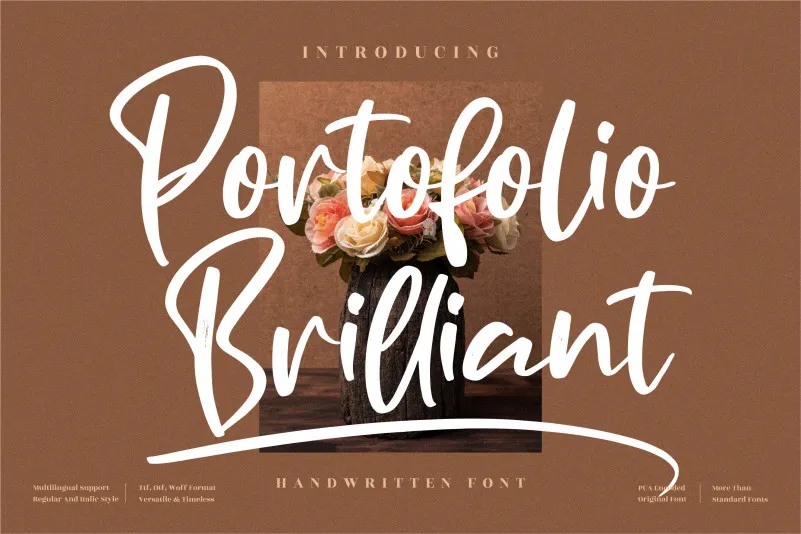
Aqui está uma descrição em português para a página de download da fonte ‘Portofolio Brilliant Font’, seguindo as instruções: Esta é uma linda e delicada fonte escrita à mão que transmite elegância e classe. Introduzida especialmente para os designers que procuram um aspecto sofisticado e revitalizante em suas criações. Perfeita para aqueles momentos em que você precisa reavaliar a aparência de seus trabalhos, oferecendo uma solução refinada e moderna. Ideal para aplicação em nomes, títulos ou qualquer tipo de texto gráfico, esta fonte será o toque final perfeito no seu design. Em um mundo de criações digitais cada vez mais complexas, é sempre bom lembrar que a simplicidade pode ser realmente poderosa e refrescante. A Portofolio Brilliant Font oferece precisamente isso: uma maneira suave e elegante de dar um novo ânimo aos seus designs, tornando-os únicos e memoráveis. Seja em uma empresa moderna ou na criação de um projeto pessoal, esta fonte não apenas atende a sua necessidade, mas também oferece um toque autêntico e único ao seu trabalho.